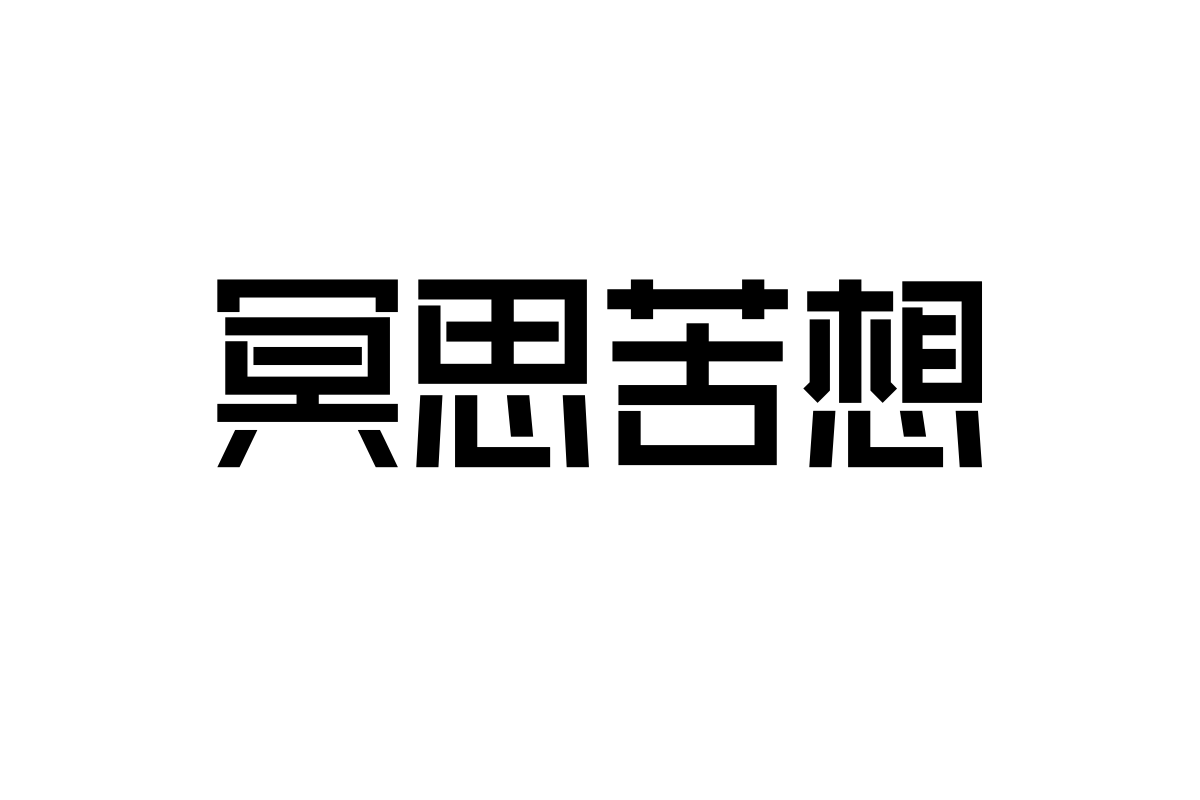
上首力方体是一款由上海首力文化传媒有限公司设计开发的字体。这款字体以其独特的设计和风格,深受广大设计师和用户的喜爱。
上首力方体的特点在于其简洁明了的线条和结构,使得整体看起来更加现代和时尚。它的笔画粗细适中,既有力量感又不失柔和,适合用于各种类型的设计作品中,如标志、名片、海报、广告等。
此外,上首力方体还具有一定的可读性,即使在不同大小和距离下也能保持清晰易读的效果。这使得它在商业应用中具有较高的实用性。
总的来说,上首力方体是一款具有独特风格和广泛应用前景的中文字体,无论是在设计还是印刷领域都有着广泛的应用空间。